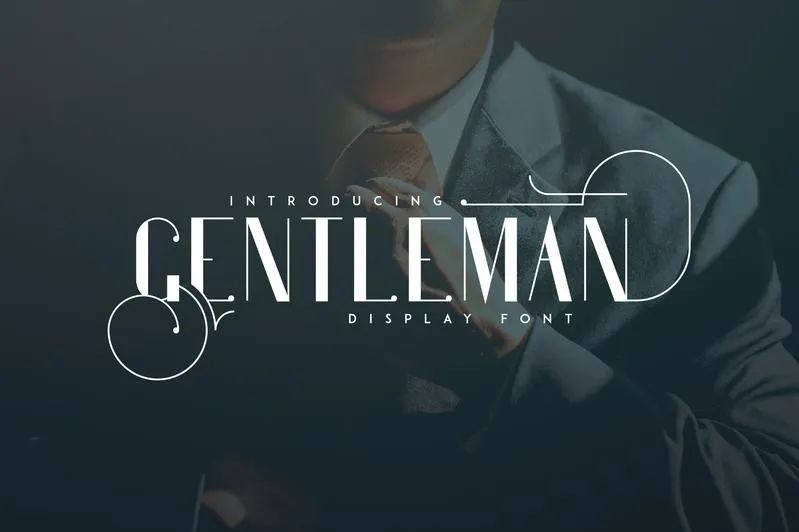
Gentleman Font + 10 Logos – Download Grátis
A Gentleman Font é uma elegante fonte expositiva que oferece três alternativas de caracteres para cada letra. Perfeita tanto para projetos de marca quanto para designs domésticos e embalagens de produtos, ela também se destaca como um ótimo estilo para cartões de casamento, convites para festas, cabeçalhos de revistas ou até mesmo como overlay texturizado sobre qualquer imagem de fundo. Ideal tanto para ambientes digitais quanto impressos, essa fonte é versátil e capaz de adaptar-se a diversas aplicações, tornando-a um recurso valioso no processo de criação. Seja eletrônico ou físico, ela se destaca com uma elegância única, garantindo que seu design seja notável e impactante.